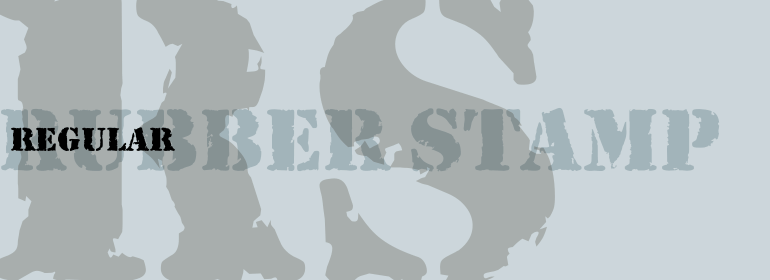
Rubber Stamp™
字体品牌: ITC(Monotype) 设计师:Birch,Alan 字体分类:衬线体 字体属性:外文 字符集:Unicode 发布时间: 2018
这一引人注目的设计是由英国艺术家Alan Birch于1983年创建,它传达了模板或橡皮图章在纸上所有的即时性、冲击力和效果。Rubber Stamp具有一种被腐蚀的、粗糙的边缘的感觉,给人一种类似于20世纪90年代在设计师中流行的老式的、破旧的打字机字体的印象。Rubber Stamp是全大写字体,主要适用于许多使用较大尺寸的标题和显示应用。试试在杂志、时事通讯,以及任何其他通过模板或橡皮图章来增强效果的工作中使用Rubber Stamp。
Created in 1983 by British artist Alan Birch, this dramatic design conveys all the immediacy, impact, and effect of a stencil or rubber-stamp on paper. With a corroded, rough-around-the-edges feeling, Rubber Stamp gives an impression similar to the old, beat-up looking typewriter fonts that were popular among designers during the 1990s. Rubber Stamp is an all caps font, and is primarily suited for many headline and display applications that use larger point sizes. Try out Rubber Stamp in magazines, newsletters, and any other work that would be enhanced by a stencil, branding, or rubber stamp effect.